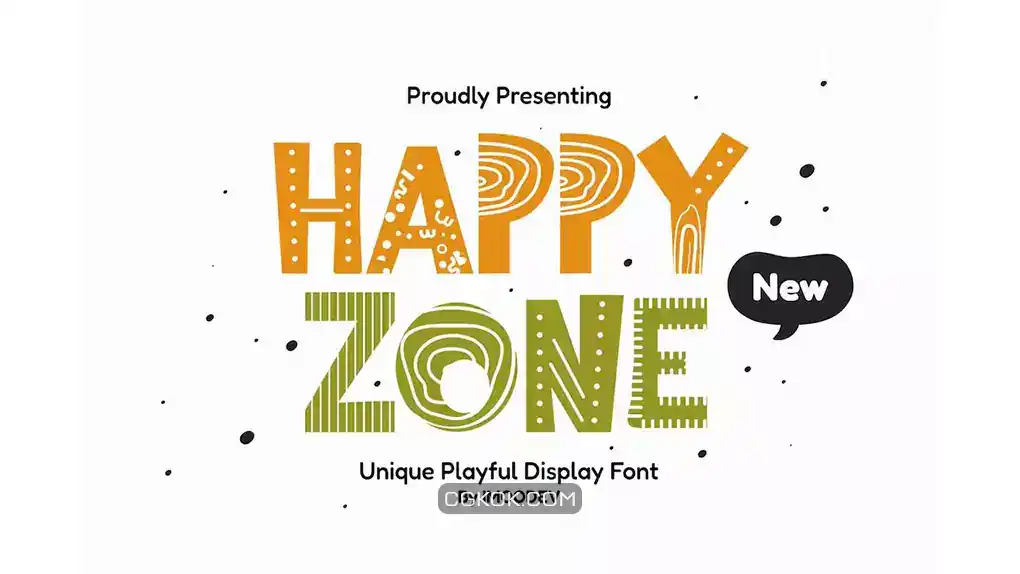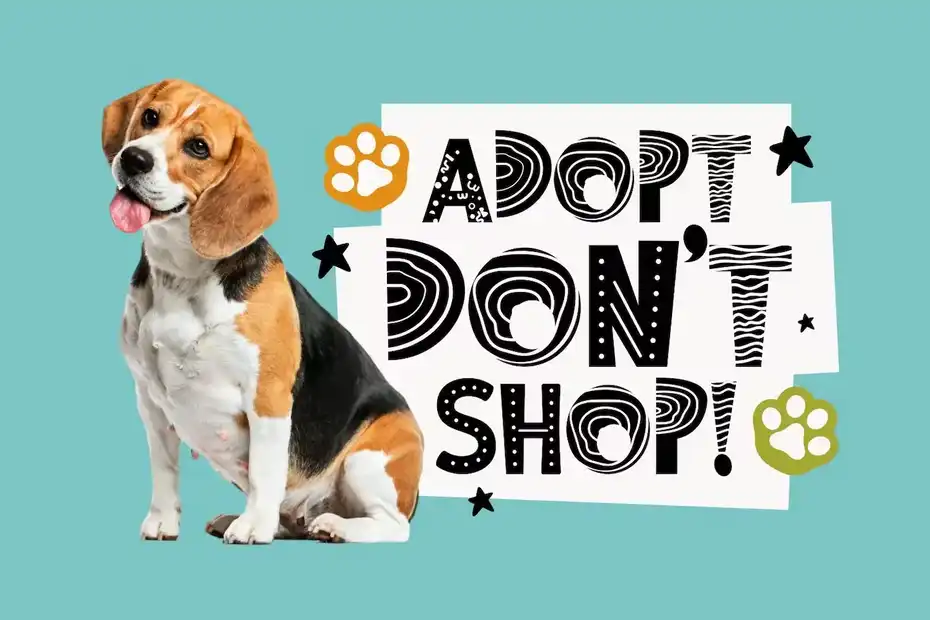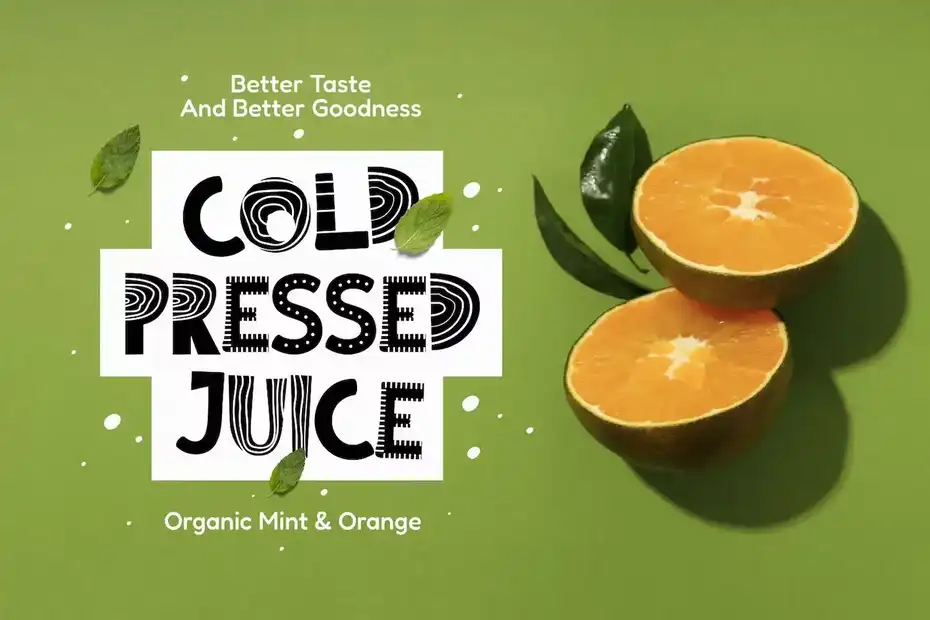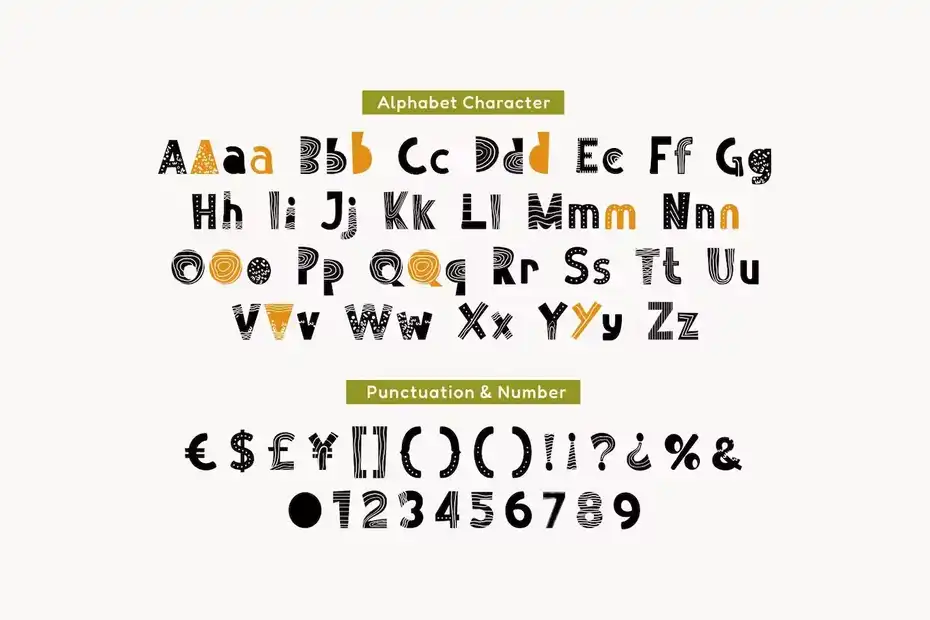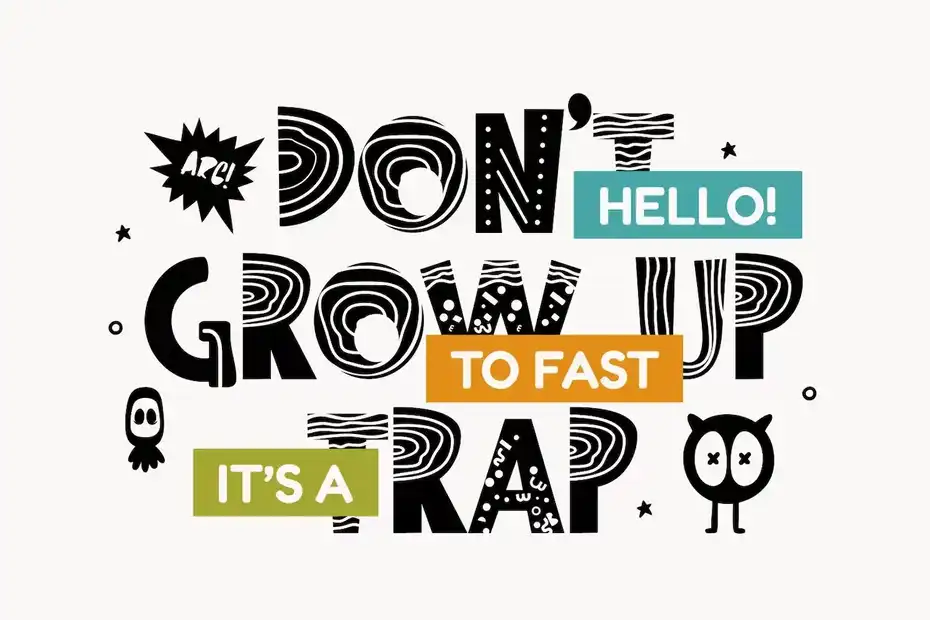
دانلود فونت‌ جالب و سرگرم‌ کننده Happy Zone – Cool Fun Fonts
دانلود فونت‌ جالب و سرگرم‌ کننده Happy Zone – Cool Fun Fonts : این مجموعه شامل یک فونت فانتزی است که برای لوگو، دعوت نامه، برندینگ، مجله، عکاسی، بسته بندی محصول، نقل قول، پوستر، برچسب، امضا، کارت عروسی، آرت دکو و غیره مناسب میباشد.